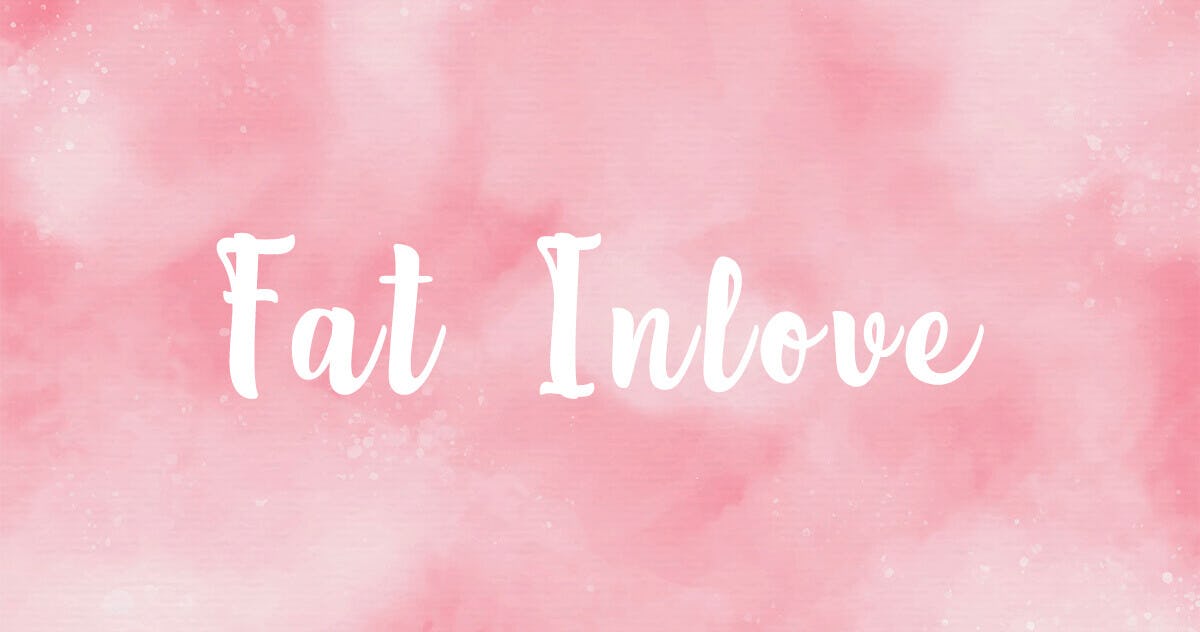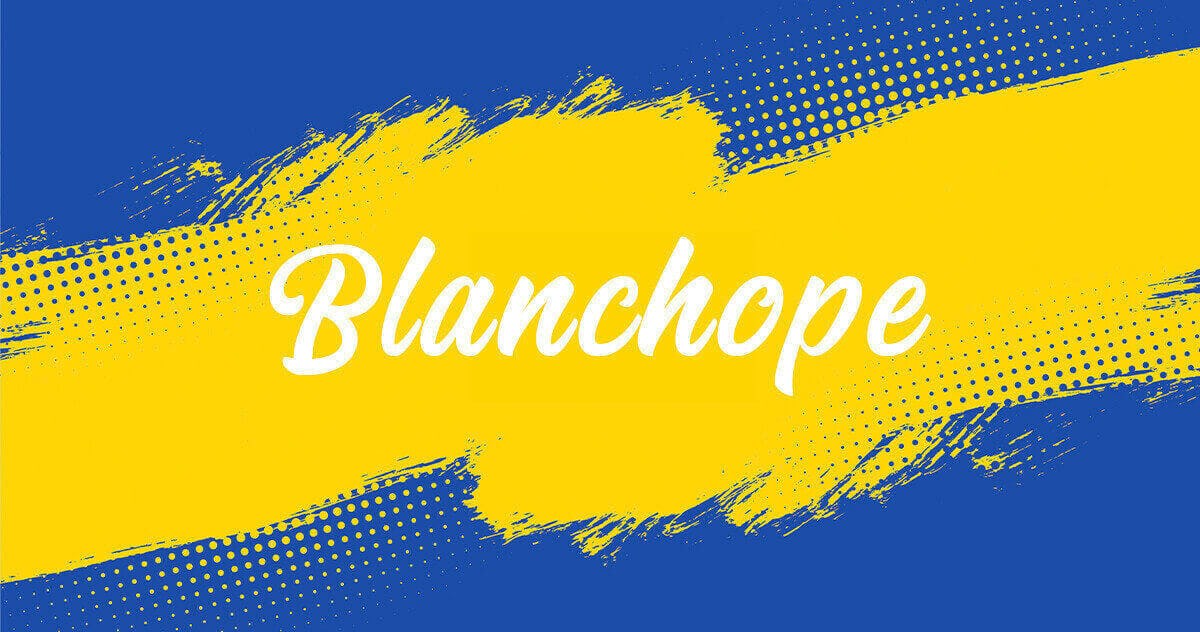
Las mejores tipografías pincel para tus diseños creativos
¿Eres de los que les gusta crear cosas nuevas? ¿Te apasiona marcar la diferencia con tus diseños y creatividad auténtica? Las tipografías comunes ya pasaron de moda.
Si estuviste, estás o piensas hacer tus diseños con tipografías como Comic Sans, Times New Roman, Arial o Century Gothic ¡Detente! 🚫
Tenemos estas opciones de tipografías pincel que le darán vida a tus diseños y renovarán tu estilo este 2021.
👉🏻 Si quieres empezar a escribir con las tipografías pincel, te recomendamos ir de frente al punto 2.
¿Qué es la tipografía pincel?
Las tipografías pincel son un tipo de fuente digital que simula la escritura manuscrita de un pincel.
Su forma es menos monótona a comparación de las otras tipografías, porque los trazos que tienen las tipografías pincel son más espontáneos.
Se le conoce también como tipografía brush que es el mismo tipo de fuente, pero traducida al inglés.
Las fuentes pincel se conocen también como tipografía estilo pincel y existen diferentes tipos de trazados para explorar toda la creatividad posible.
La letra tipo pincel fue creada pensando en trasladar los diseños físicos de escritura a una herramienta digital y con acceso en la plataforma web.
Se utiliza para diferentes momentos y espacios como tipografía para tarjetas de presentación, tipografías para logotipos, diseños gráficos, publicidad, revistas, películas, entre otros.
10 diseños de tipografías pincel
Hay diferentes modelos de tipografías brush para combinar con muchas texturas. Dependiendo del uso que le darás a la tipografía puedes elegir un determinado diseño.
Te traemos 10 diseños de tipografías pincel que puedes utilizar para salir de tu zona de confort gráfica y atreverte a hacer algo distinto y único.
Estos diseños de letras para escribir te las presentamos como tipografías elegantes para descargar que te servirán para tener más opciones en tu portafolio tipográfico.
1. Birdlove
Esta tipografía brush tiene la silueta de un pincel y maneja las letras de corrido, es decir unidas entre sí. Tiene un diseño bonito que puedes utilizar en títulos o frases, perfecta para decorar tus gráficas.
En la fuente Birdlove están registradas todas las letras en mayúscula y minúscula, los número y signos. Sin embargo, las tildes no se pueden utilizar en esta fuente pincel.
2. Authentic Signature
Authentic Signature es una de las tipografías pincel más fina y con letra corrida. Tiene líneas particulares que la hacen una fuente elegante y perfecta para hacer textos.
Simula una letra manuscrita y tiene el registro de todas las variaciones de letras y signos, también cuenta con la tilde en todas las vocales mayúsculas y minúsculas. Es una fuente pincel completa.
3. Hey August
Esta tipografía brush tiene un estilo más marcado de pincel. Se logra ver la textura de los lienzos en las letras y los espaciados que simulan una pintura real.
Hey August es una fuente pincel completa, porque tiene todas las letras, números, signos, puntuación y tildes registradas.
4. Watone
Esta tipografía pincel es parecida a la anterior, pero su diseño es más marcado. Las letras chorreando pintura hacen más real esta tipografía.
Watone no tiene registradas las letras minúsculas, toda la fuente se escribe en mayúscula. Tiene disponible todos los signos de puntuación y números, menos las tildes.
5. Atos
Fuente: Freepik
Atos es una tipografía pincel mucho más particular, porque corresponde a un tipo de letra manuscrita sofisticada. Los arcos en las letras mayúsculas le dan el toque diferencial.
La fuente pincel tiene registro de todas las letras minúsculas y mayúsculas, los signos y puntuaciones. Esta tipografía pincel no cuenta con tildes en las letras.
6. Fat Inlove
Fuente: Freepik
Fat InLove es una tipografía pincel con un estilo de letra más decorada. El diseño manuscrito es de corrido y la tipografía es alargada hacia arriba con poco espaciado.
Esta fuente pincel es completa, tiene todas las variaciones de letras, signos, tildes y puntuaciones. Sin embargo, al descargarla no incluyen las decoraciones de gotas en los extremos.
7. Blanchope
Blanchope es una tipografía pincel con letra corrida. La silueta es curvada y termina ligeramente con un doblez.
Esperamos hayas disfrutado así como nosotros este blog. Recuerda que estas tipografías pincel son solo una pequeña muestra de todo lo que puedes encontrar en las plataformas que te recomendamos 🙌🏻
Navega por la web, identifica la tipografía pincel que más te gusta y úsala como quieras.